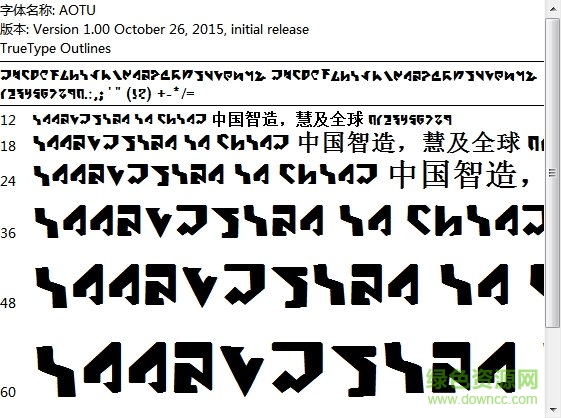
凹凸文字體庫民間版
凹凸字體是以凹凸世界文字為模板創(chuàng)作的凹凸文字字體庫【民間版】,讓廣大凹凸迷們可以感受最逼真的視覺效果,給你的手機(jī)字體閱讀帶來更親切體驗,綠色資源網(wǎng)獨家推薦!
凹凸世界字體說明
畫凹凸同人的小伙伴們,還在為模仿官方而努力去翻凹凸文字對照表而心累嘛?
不用擔(dān)心!這里已經(jīng)把超級方便的凹凸文字字體庫【民間版】做出來啦!
因為是民間版,制作的并沒有官方的精細(xì),字體之間會出現(xiàn)輕微的高低錯落的感覺,請見諒!